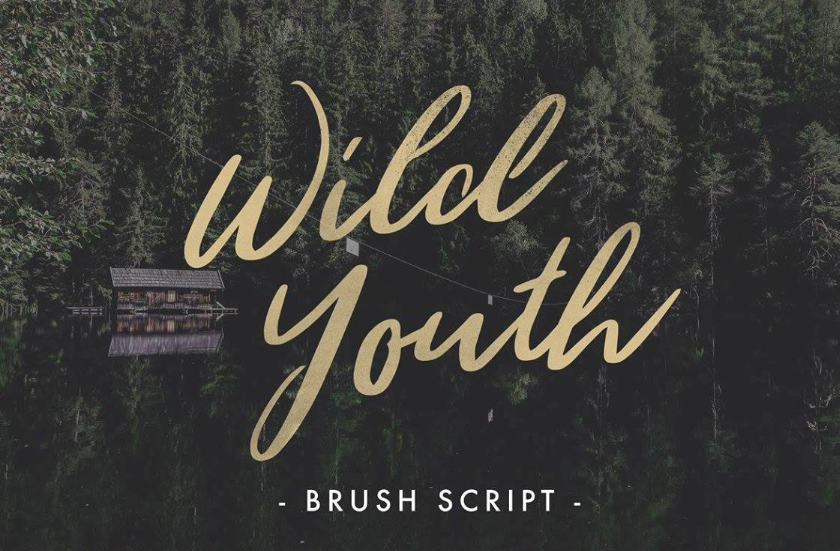
Wild Youth Font – Download Grátis
Wild Youth é uma elegante e feminina fonte de script escrita a mão, desenvolvida manualmente com o auxílio de uma caneta-pen. Ela é perfeita para criar identidades empresariais e logos, adesivos, scrapbooking, cartas de casamento, frases motivacionais e tags. Este design foi criado pelo designer Jeremy Vessey. Wild Youth Font se destaca entre as fontes Brush Fonts por sua fidelidade ao estilo elegante da escrita a mão, oferecendo um toque sofisticado que combina bem em diversos ambientes de design. Com suas linhas delicadas e seu caráter feminino, esta fonte adquire um charme único capaz de dar vida a qualquer projeto que ela seja utilizada. A sua utilização pode ir desde frases em cartas de casamento até letras finas em elementos decorativos de scrapbooking. Ainda mais, as suas propriedades levemente onduladas e fluidas fazem dela uma escolha ótima para adesivos e tags em que é necessário um toque suave e delicado. Com certeza, Wild Youth Font se torna um recurso valioso tanto para designers profissionais quanto para aqueles amantes de design iniciantes. Suas características distintivas a tornam uma fonte indispensável para qualquer designer buscando trazer personalidade e fidelidade ao seu projeto.